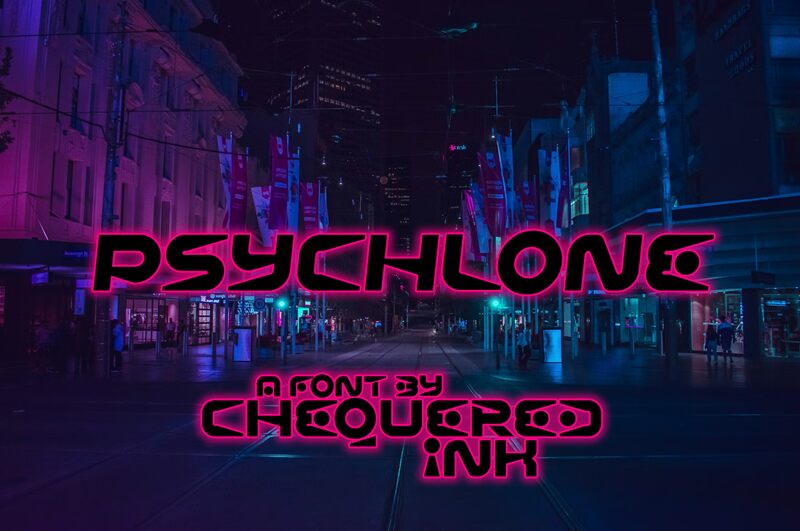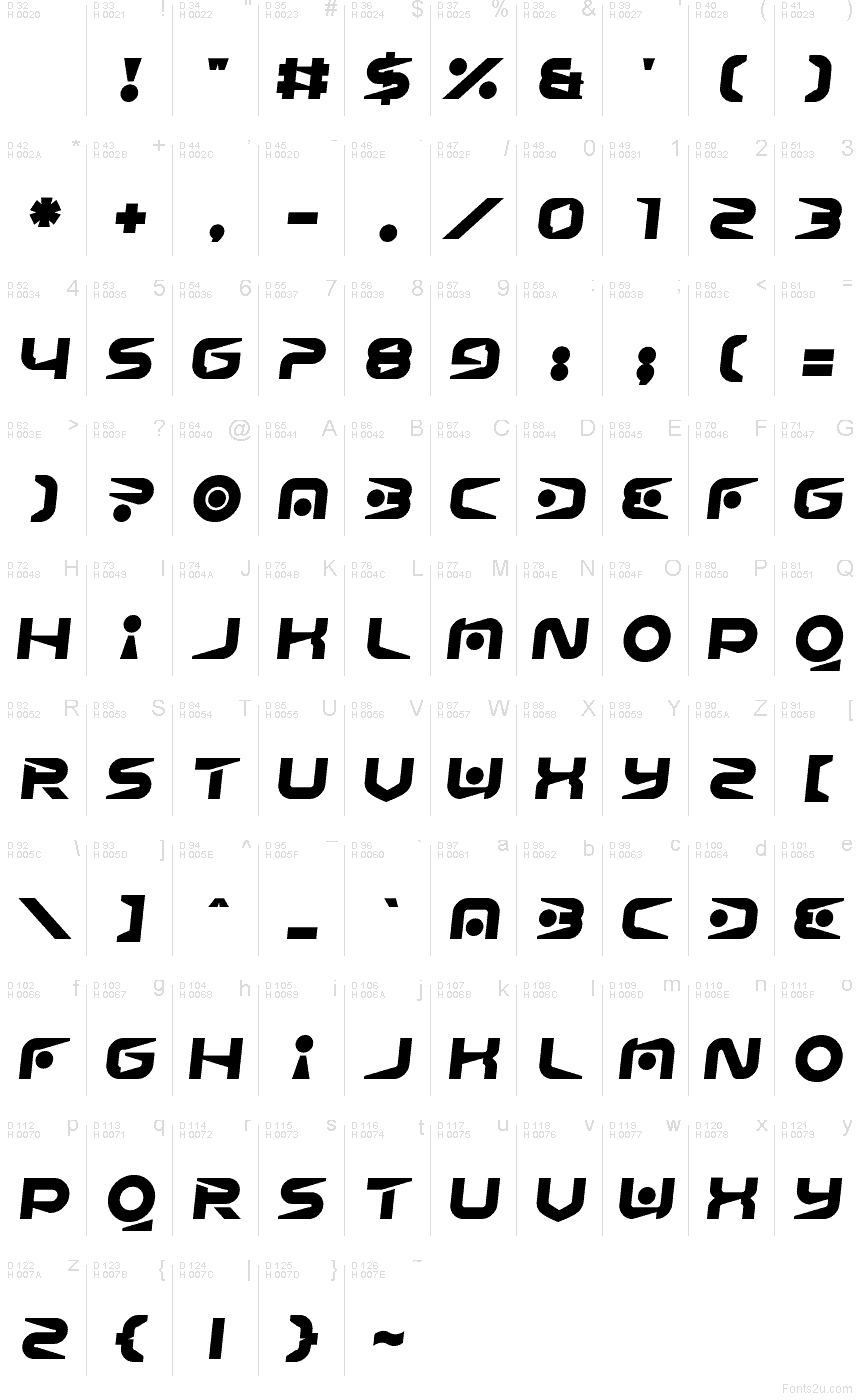
Psychlone od Chequered Ink to darmowy, futurystyczny krój pisma typu display, składający się z wielkich liter, o szybkim, sci-fi charakterze. Litery opierają się na ciętych krzywiznach i ostrych przekątnych, dzięki czemu cały projekt sprawia wrażenie ruchu zatrzymanego w grubych, kompaktowych formach, a nie neutralnej geometrycznej konstrukcji.
Naturalnie pasuje do logotypów gier, grafik do muzyki elektronicznej, nagłówków plakatów, brandingu technologicznego oraz tytułów, gdzie kilka słów potrzebuje naładowanego, syntetycznego pazura. Jako darmowy font, świetnie sprawdza się również w krótkich tekstach okładkowych i monogramach, ponieważ wycięte łączenia i klinowate kąty sprawiają, że nawet krótkie hasła wydają się aktywne i mechaniczne.